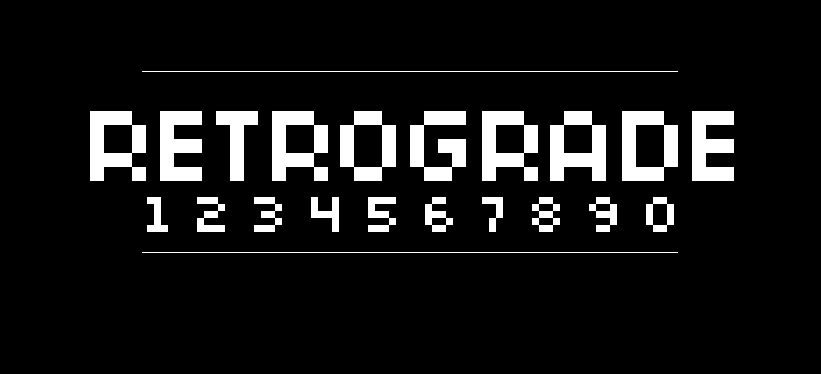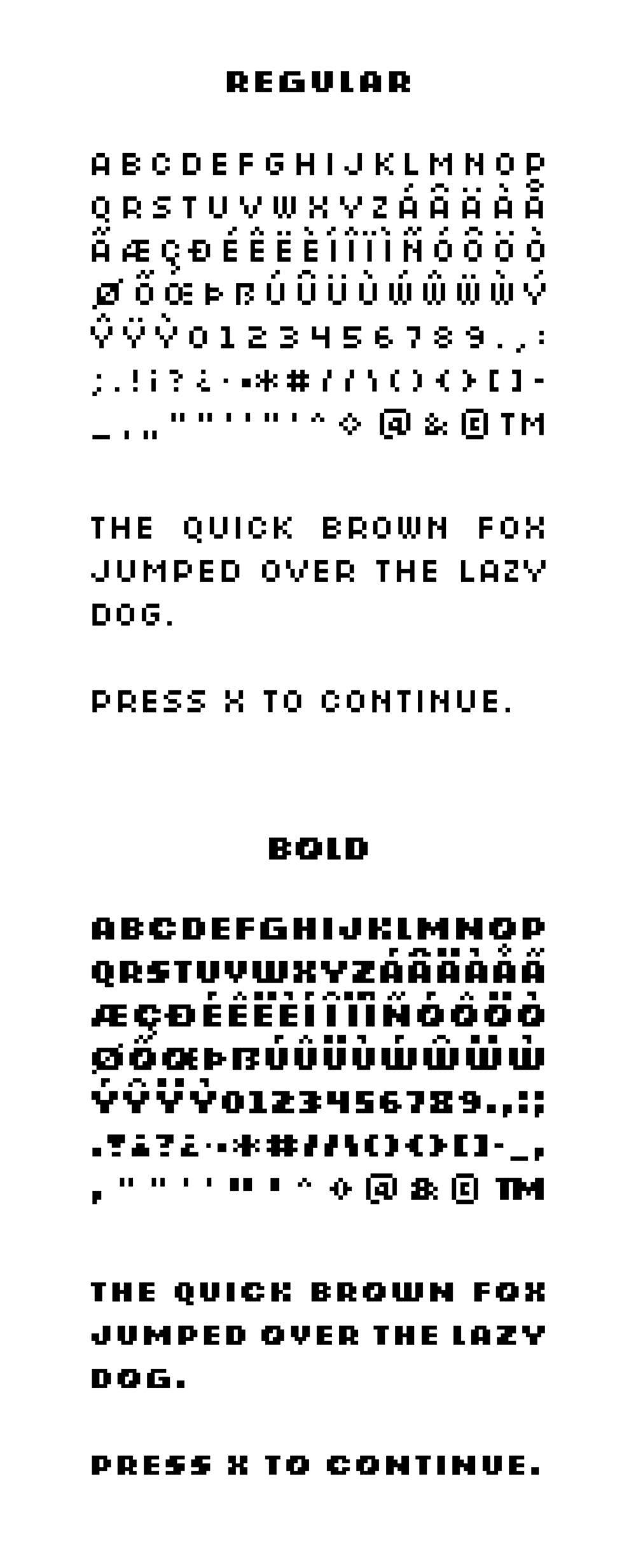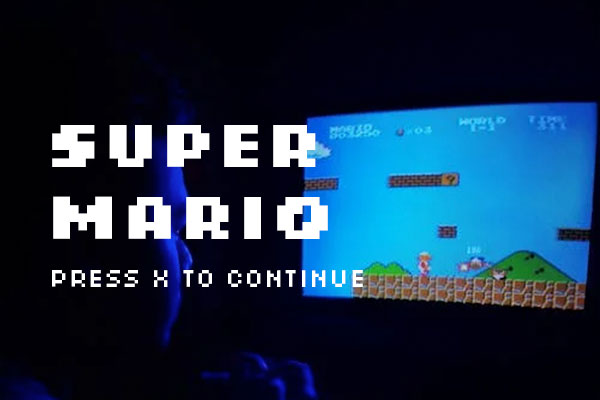
Retrograde字体介绍
Retrograde的作者是美国的Daler Mukhiddinov,该字体是一款强大而简单的像素风格英文字体,具有2个字重。
Retrograde字形简单可爱,让人很容易联想到小时候玩红白游戏机上显示的文字,希望该字体能给你带来美好的回忆!
Retrograde字体应用示例